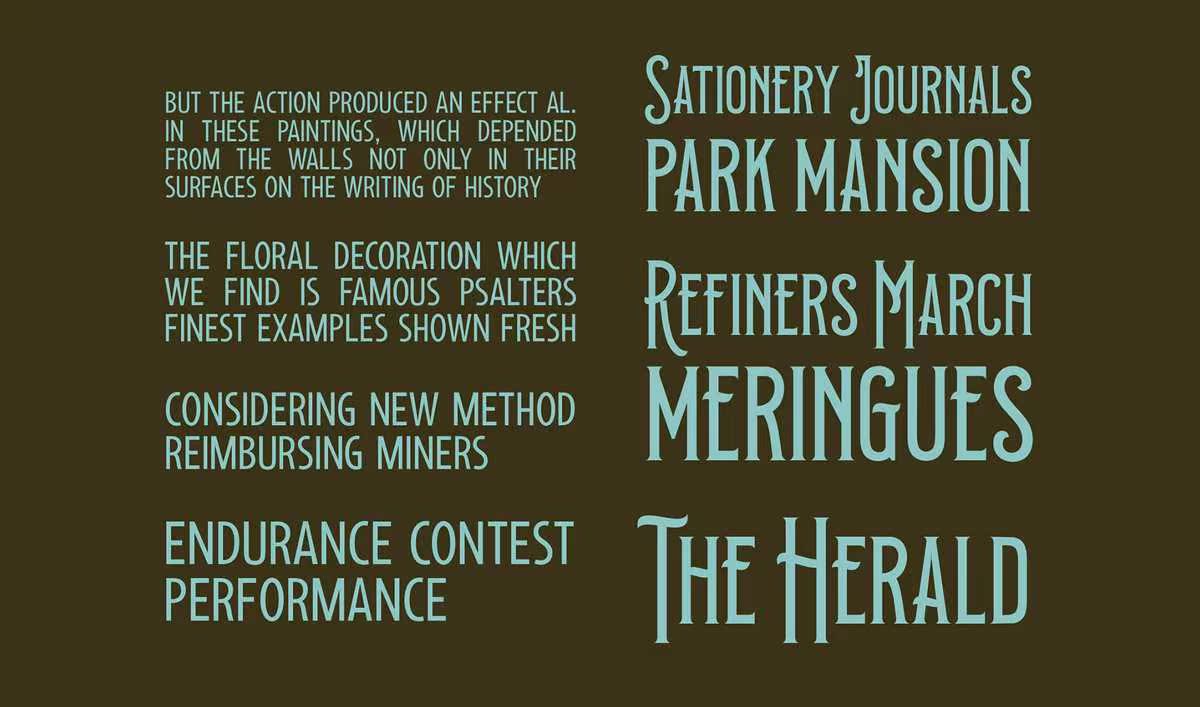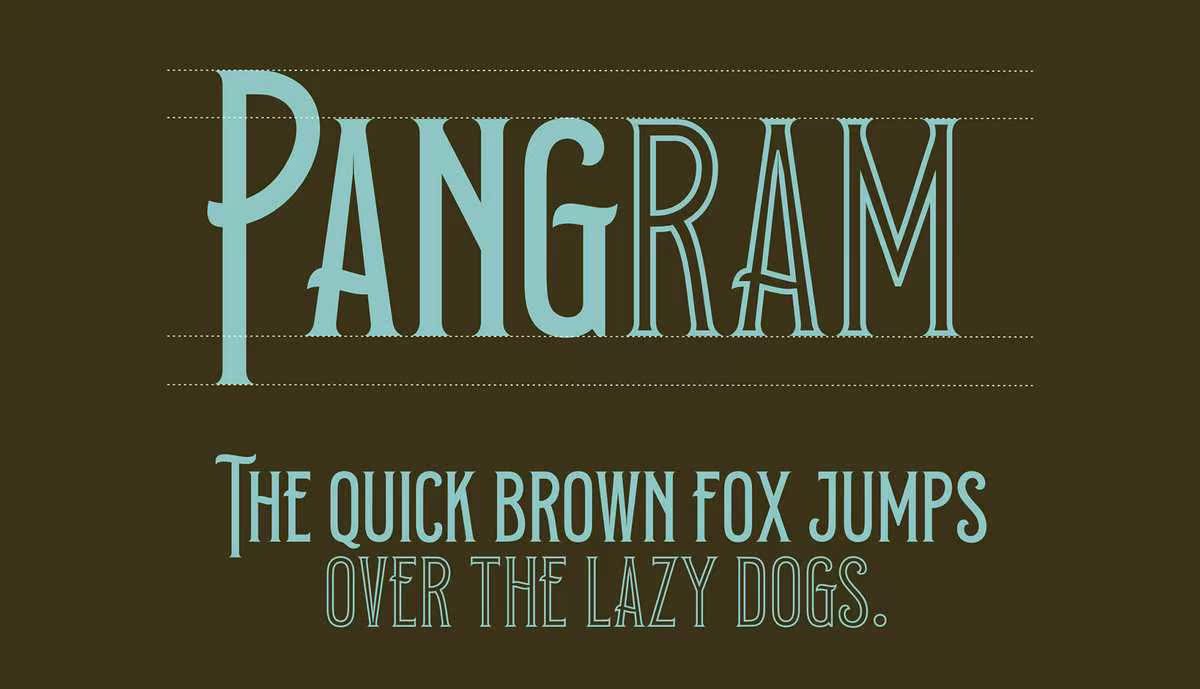
ProdeltCo–采用了源自于商标的浓缩字体和受产品所用的经典标签启发的三种风格。这些特征反映在所有字体中,并定义了所有字体的细节和颜色。各种可选样式都有多种多样的设计选项,完美地适用于标题、徽标、海报、包装、,T恤、明信片和更多产品。ProdeltCo–采用了源自葡萄酒标签的浓缩字体,以及受产品所用的古典安全带启发而设计的Trostyles。这些特征在所有字体中都得到了体现,并定义了所有字体的细节和颜色。不同的可选款式都有多种设计选项,并完美地用于标题,徽标、海报、包装、T恤、明信片等。